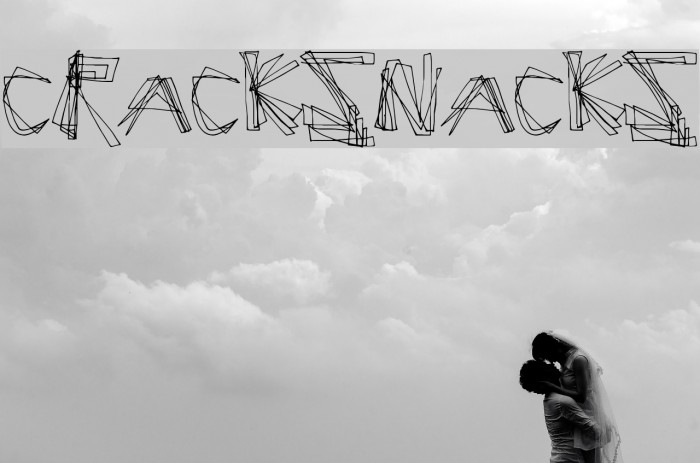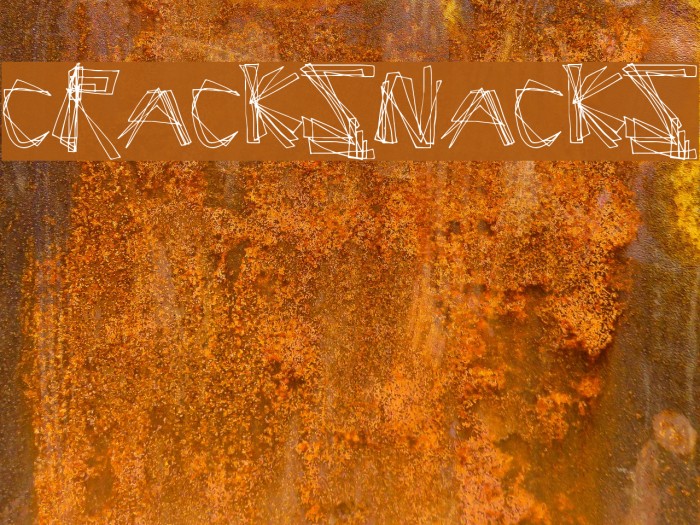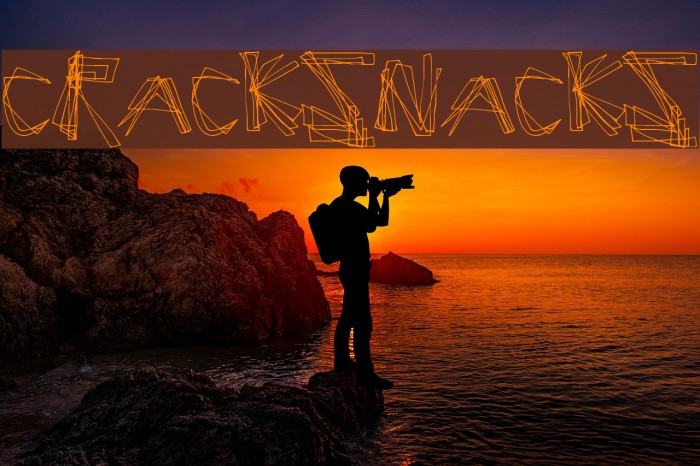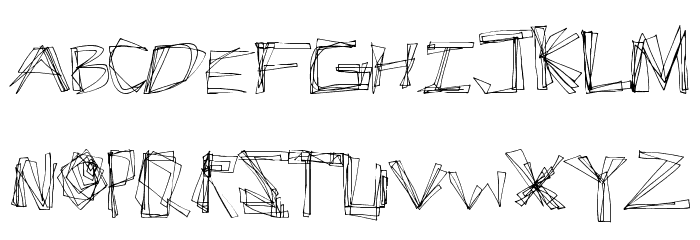
CrackSnacks Font
| Estilo geral | Avant-garde, Artistic |
| Caso de uso | Logos, Posters, Creative Branding |
| Projetos propostos | Ideal for artistic projects, album covers, posters, and creative branding that seeks to make a bold statement. |